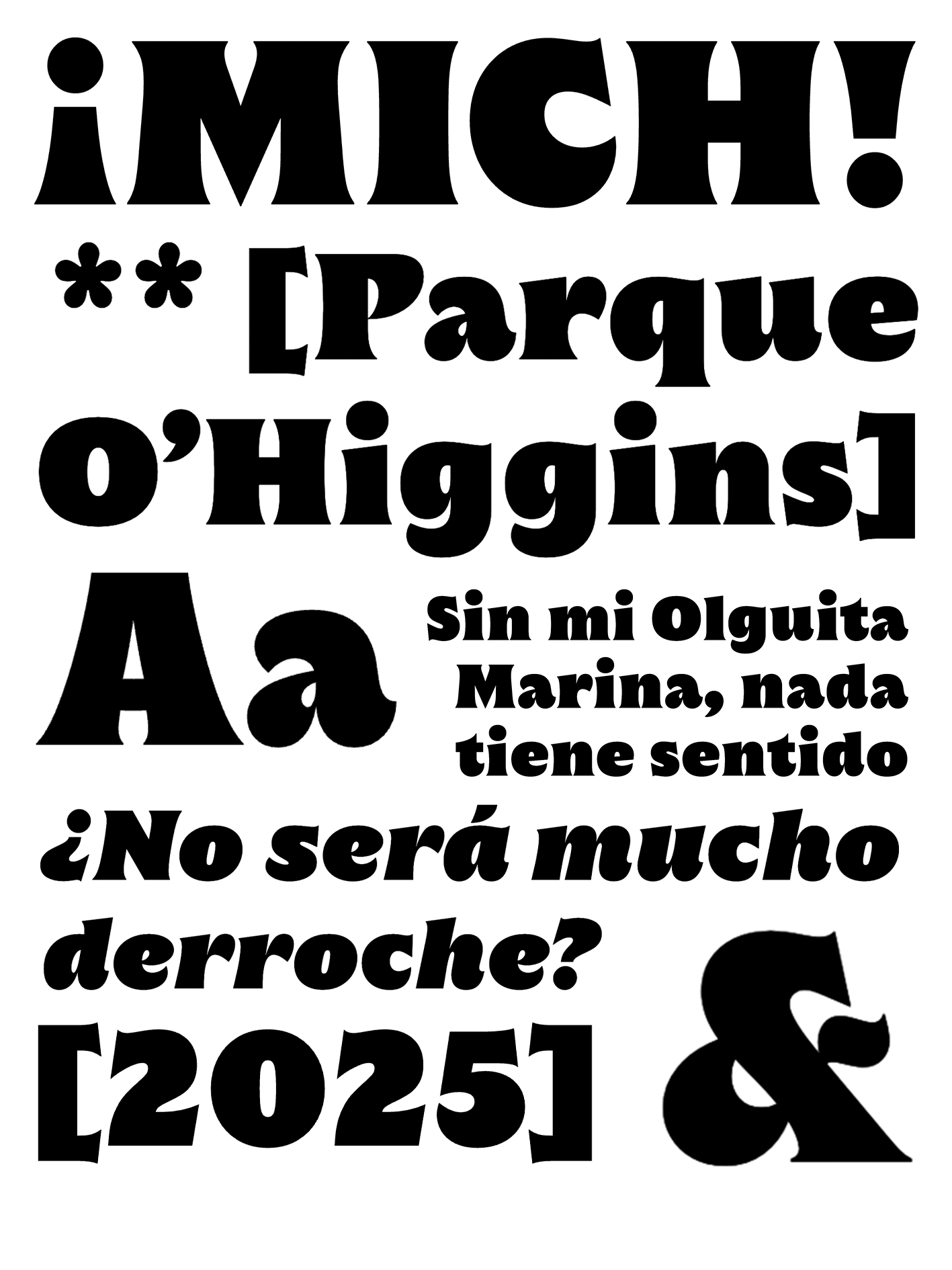
| Descripción | Baile es una tipografía con serif de estilo display, inspirada en ITC Benguiat, rediseñada con proporciones ajustadas, terminales distintivos y un estilo extrabold para otorgar mayor peso visual. Su personalidad decorativa y formas de letra únicas la convierten en una opción ideal para titulares llamativos, portadas de libros, afiches y diseños editoriales. Disponible en estilos Regular e Italic, ofrece versatilidad para una amplia gama de aplicaciones creativas. |
| Familia(s) | Baile regular, Baile Italic |